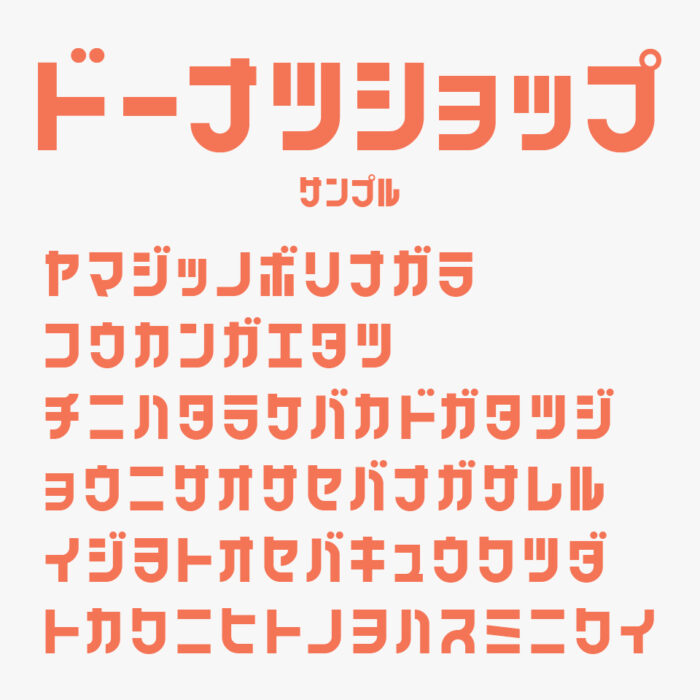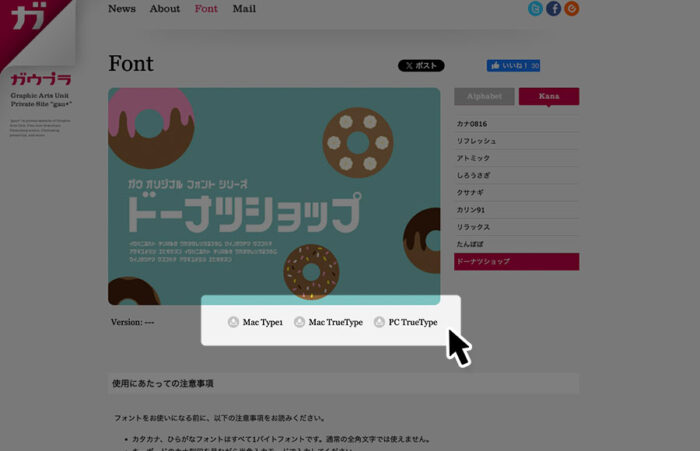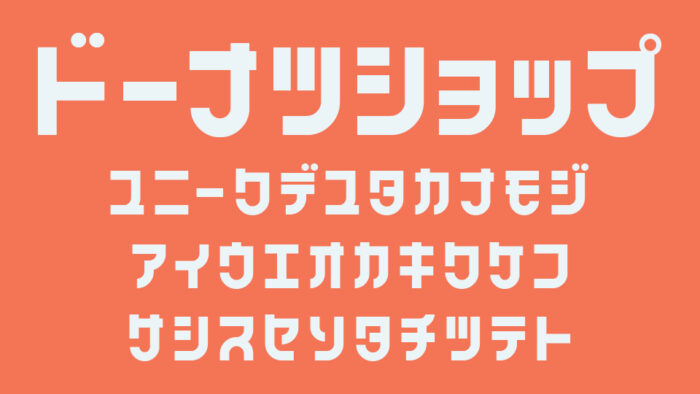
ドーナツショップフォントは、丸みを帯びた形状に直線的な処理が加わった、ユニークなデザイン系のカタカナフォントです。
フォント名のようにドーナッツの甘さと可愛さを感じる柔らかさと、少し長体フォルムで、都会的でスタイリッシュな雰囲気を同時に持ち合わせており、その名の通りポップで親しみやすいデザインです。
収録文字は、カタカナが収録されています。